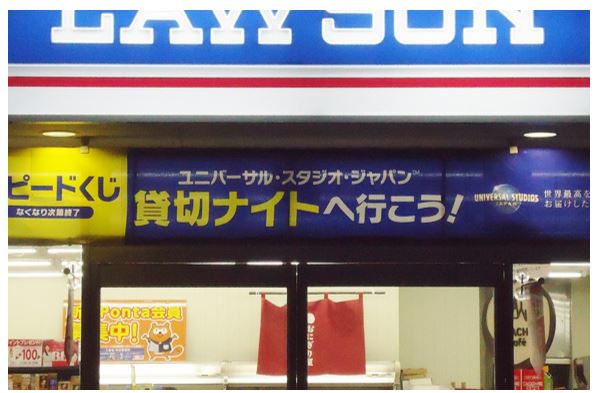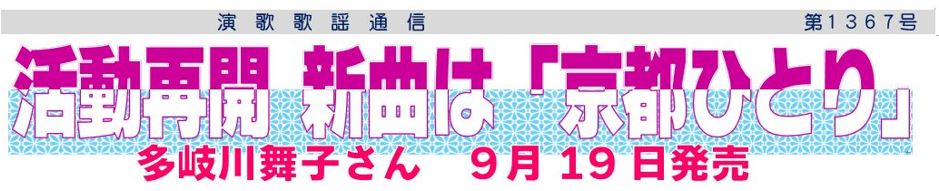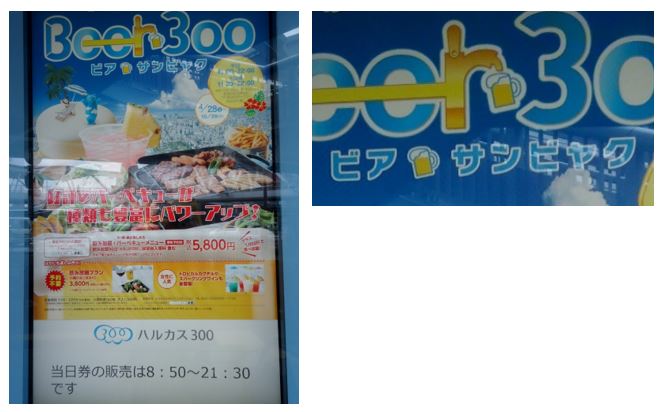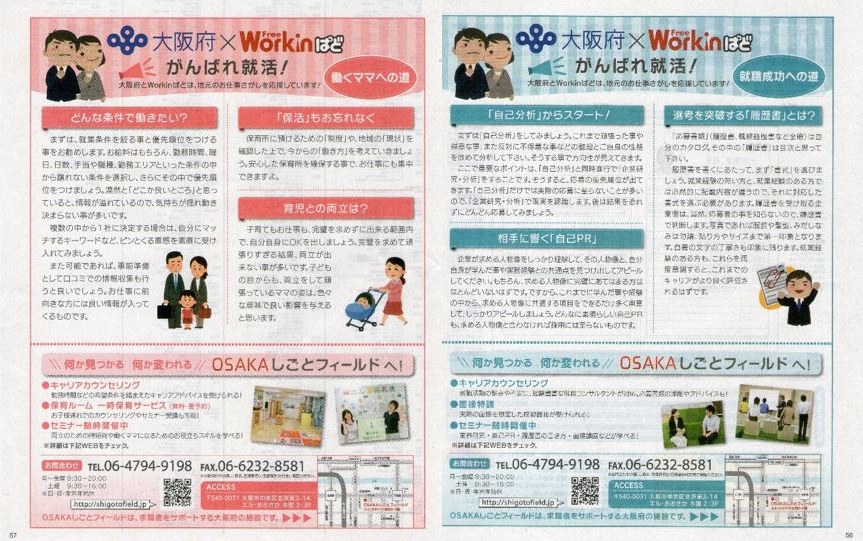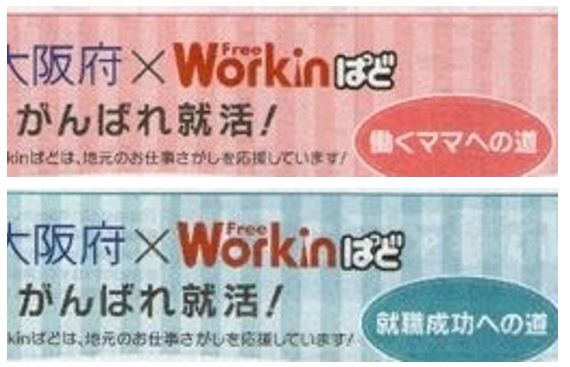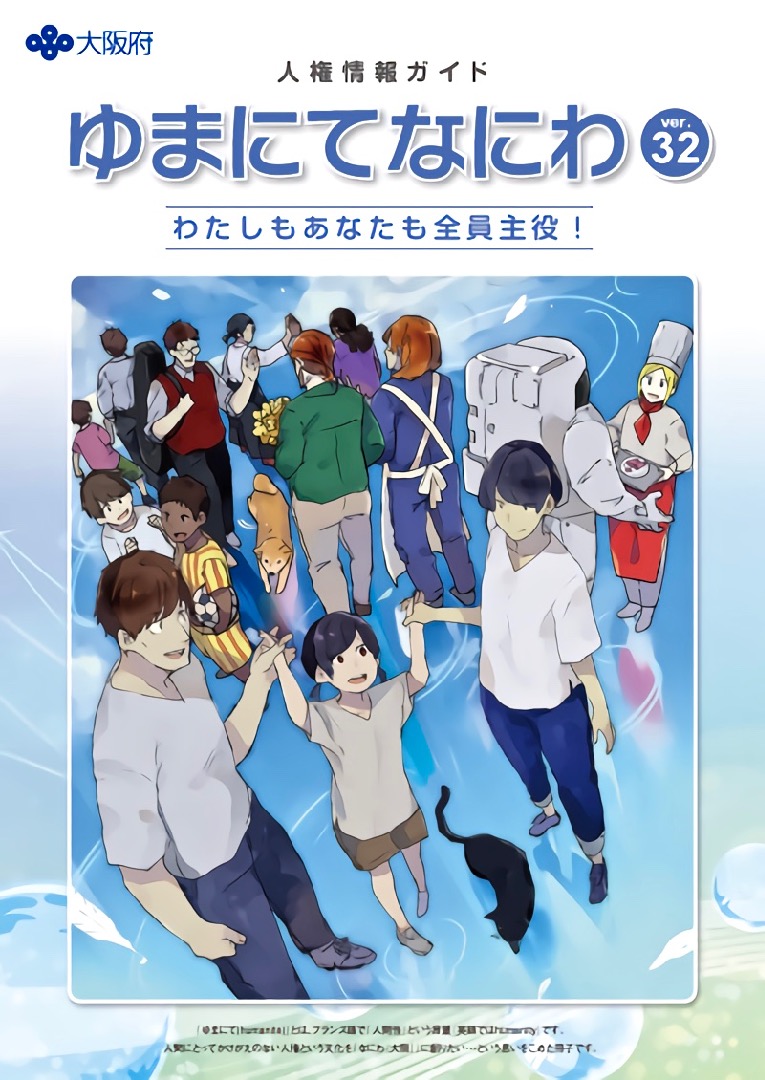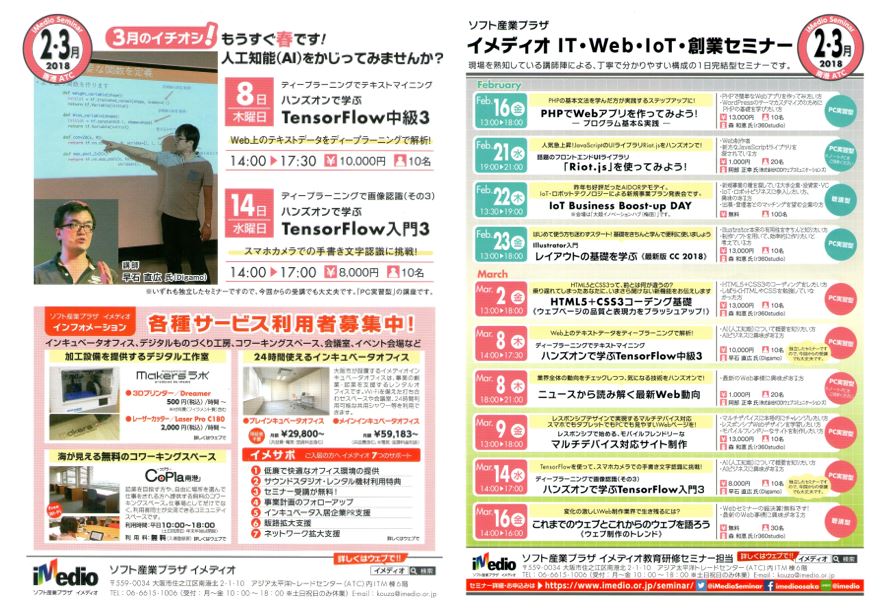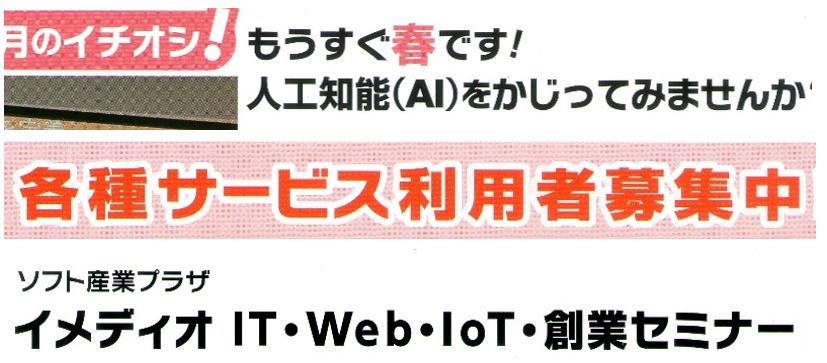
自社広告 大阪のうめ吉
サンリオが、自社出版書籍に掲載した「ブルーレイシリーズ」の自社広告。
ロゴタイトルとその下中央部分。
カラオケ 大阪のうめ吉
大阪市平野区のカラオケ店の折り込みチラシです。
キャンペーンのロゴタイトルの部分。
ライセンスものです。
べイエリア情報誌 大阪のうめ吉
ベイフロント・アジア太平洋トレードセンターが発行するB5判16ページ、大阪ベイエリアの情報誌10・11月号です。
表紙の記事案内(写真内左上)と本文(右側2枚)で2ページにわたって使用しています。
東住吉区広報 大阪のうめ吉
大阪市東住吉区の「広報なでしこ」10月号です。
12ページ(面建て)の1面で、区民フェスティバルの告知です。
モリサワさんにライセンスされた、かなフォントのようです。
「フェステバル」の部分ですね。
ベイエリア情報誌 大阪のうめ吉
大阪のベイエリア情報を載せた情報誌「ベイエリアNOW」10・11月号の表紙です。
省略しましたが、本文でも2ページにわたって使われています。
B5判16ページものです。
STVキャンペーン 大阪のうめ吉
Twitterでの、郷里北海道のフォロワさんのツイートにのっていたアドレスにアクセスしたものです。
北海道の放送局STVの「北海道は元気だよ!」キャンペーンのタイトルです。
看板 大阪のうめ吉
大阪市平野区、空洞コンクリートブロックをはじめ、エクステリア(門扉とか、屋外の構造物)関連物の製造、販売、施工を手がけている会社の平野営業所の看板です。
文字間隔が、ちょっと詰め過ぎな感じですね…。
生協カタログ 大阪のうめ吉
おおさかパルコープ、大阪よどがわ市民生協が組合員に配布しているカタログです。
小説の扉ページ さとうゆたか
小説 野性時代2018年9月号 Vol.178。
●連載小説 坂木 司 ホテルジューシー2
工事現場の看板 さとうゆたか
ニタラゴルイカをアウトラインシャドウ処理してある。
近所の千住関屋ポンプ所の工事現場入り口。